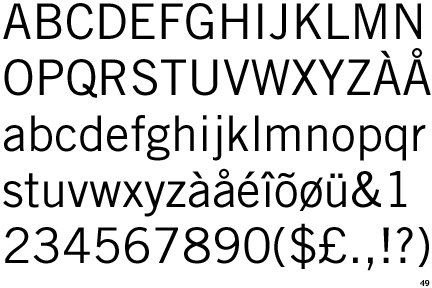
Brainstorming: Passende Antiqua zu Trade Gothic?
Mir wurde eben aufgetragen, einen Rückblick von dem, für das ich 2 Jahre gearbeitet habe, in Buchform zu gestalten.
Beschämt muss ich sagen, dass ich in diesen 2 Jahren keinen Gedanken daran verloren habe, eine passende Antiqua zu unserer Hausschirft Trade Gothic zu suchen, einfach weil es dafür bisher keinen Anlass gab.
Das Buch damit zu setzen wäre allerdings äußerst gewagt, die Zurichtung ist mir einfach zu unruhig, und die Textmenge ist immens, und nun suche ich nach einer Serifenschrift, die »passt«. Die Titel, Marginalien, Kolumnentitel, Pagina, etc. werden wahrscheinlich in Trade gehalten (optische Linie durchziehen), Lesetext sollte aber in Antiqua sein.
Ich blättere am Nachmittag meine Musterbücher durch, aber vielleicht hat auch hier jemand spontan eine nette Idee?
Idealerweise hat die Schrift ähnliche Proportionen (könnte sein dass die Trade auch in der selben Textgröße dargestellt wird, dann sollte es nicht kollidieren) und ist platzsparend. Eine Egyptienne wäre eventuell denkbar, wenn sie wirklich passt.
Welche Trade?
Die "roman" ist ja sehr licht. Die "bold No. 2" recht dunkel. Dazwischen fehlt beinahe eine semibold, die dann schon wieder eher eine normale bold wäre. Die "bold" ist schon ziemlich square. Ist halt keine A. Frutiger Familie.
Wenn es um die lichte "roman" geht, würde ich mir mal die Proforma 1 anschauen. Oder die Corporate A. Beide sind vielleicht etwas zu "corporate" …? Wir wissen ja nicht wie "ruhig und stilisiert" der Text werden soll.
Die Utopia ist für die TG regular zu dunkel, wenn sie in der gleichen Zeile funktionieren soll, finde ich. Vielleicht mal die ITC Slimbach anschauen, oder die Kepler, bei der könnte man tricksen wegen der unendlich vielen Schnitte und Gewichte.
Vorstellen könnte ich mir noch Elektra*, ganz vielleicht die Erhardt, noch ganz vielleichter die Janson Text, obwohl die wieder zu dunkel ist, hehe.
Zum Abschluss:
Es ist die Kepler geworden.
Titel: 16pt Trade Gothic light
Zwischenüberschriften: 9,3pt Trade Gothic Bold No.2
Fließtext: 10pt Kepler Semicondensed caption
Das hat nicht nur ästhetische Gründe... Schlussendlich brauchte ich eine neutrale, unauffällige, robuste, platzsparende Serifenschrift, die von den Proportionen her passt und genug Diversifikation (Gewichte, Kapitälchen, Ziffernformen, ...) erlaubt.